40 Font Terbaik untuk Situs Web (Gratis dan Berbayar)
Diterbitkan: 2020-10-07Tugas menemukan tipografi untuk situs web yang Anda rancang dapat menjadi hal yang menakutkan. Pada saat penulisan artikel ini, ada lebih dari 1.000 keluarga font Google, hampir 2.000 font Adobe, 15.000 font di Fonts.com, dan hampir 35.000 font di MyFonts.com
Dengan persyaratan tambahan untuk font, seperti pemasangan font, bobotnya, keterbacaan, rentang gaya, dan banyak lagi, tugas menemukan font yang tepat untuk situs web Anda bisa menjadi tantangan yang luar biasa, untuk sedikitnya.
Untungnya, panduan ini ada di sini untuk membantu Anda menemukan font terbaik untuk Anda. Kami telah meneliti dan menemukan 40 font terbaik untuk situs web
Mengapa Font Situs Web Penting?
Font situs web menyumbang 90% dari desain. Oleh karena itu, memilih yang tepat dengan pengetahuan sangat penting untuk keberhasilan situs Anda. Berikut adalah beberapa alasan utama mengapa:
1. Pilihan Font Mencerminkan Karakter Merek Anda
Sebagian besar pemasar mengetahui pesan merek mereka, tetapi pilihan font Anda perlu mencerminkan dan mewakili karakter merek Anda. Misalnya, font romantis seperti kaligrafi atau meme unik tidak akan mencerminkan merek Anda jika Anda memiliki organisasi amal formal.
Demikian pula, jika font Anda perlu mencerminkan bank, font lucu tidak akan membangun kepercayaan, dan pembaca Anda mungkin tidak menganggap serius merek Anda. Oleh karena itu, pilihan merek juga berkisar pada pemahaman audiens target Anda.
2. Keterbacaan dan Pengalaman Pengguna
Isu-isu ini saling terkait. Seringkali, pembaca harus menekan wajah mereka ke layar untuk membaca teks. Harus melakukannya tidak secara positif memengaruhi pengalaman pengguna mereka. Jika font terlalu kecil, prospek potensial dapat hilang dalam hitungan detik. Demikian pula, memilih font besar adalah praktik yang buruk karena mereka "berteriak" pada pembaca, yang menghalangi.
Juga, memiliki terlalu banyak font dianggap membingungkan dan tidak profesional, terutama jika mereka berada di halaman yang sama. Praktik terbaik adalah memilih maksimal dua atau tiga font untuk memastikan keseragaman dan kejelasan di seluruh situs Anda. Font tidak hanya memengaruhi pengalaman pengguna tetapi juga minat, kecepatan navigasi, dan banyak aspek lainnya.
3. Pertumbuhan Bisnis
UX berhubungan langsung dengan peluang bisnis. Jika pengunjung Anda merasa nyaman membaca konten situs Anda, mereka mungkin tinggal lebih lama dari yang direncanakan – terutama pengunjung baru.
Situs yang memberi pembaca konten menarik yang ditulis dengan font premium yang andal, menarik dan mempertahankan perhatian. Mencapai ini membantu Anda membangun kepercayaan konsumen, meningkatkan keunggulan kompetitif Anda, dan meningkatkan peluang bisnis dan keuntungan.
Font sangat penting untuk merek atau perusahaan Anda karena Anda ingin font tersebut membangkitkan emosi positif, memberikan keterbacaan yang mudah, dan meningkatkan laba Anda.
Apa Kategori Font yang Berbeda?
Ada berbagai jenis dan kategori font, dan setiap variasi memiliki tempatnya tergantung pada merek Anda. Beberapa font lebih rumit dan terlihat, sementara yang lain relatif lebih sederhana dan serbaguna.
Beberapa kategori font ideal untuk tajuk yang tebal dan menarik, sementara yang lain paling baik digunakan dalam paragraf teks yang panjang. Berbagai kategori font adalah sebagai berikut:
1. Font Sans Serif
Font sans serif adalah font tanpa tanda (Prancis: sans ) di akhir huruf ( serifs ).
Font sans serif biasanya sederhana dalam desain, yang membuatnya serbaguna dalam hal penempatan dan penggunaan. Mereka berjalan dengan baik di badan halaman atau di teks header. Mereka juga dapat digunakan untuk menjinakkan desain situs web yang tampak unik.
Jika Anda ingin memberikan teks Anda tampilan yang bersih dan minimal dan mendorong pengunjung untuk membaca halaman secara menyeluruh, maka sans serif adalah font untuk Anda.
2. Font Serif
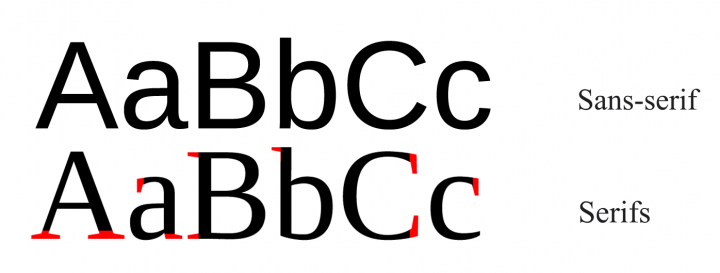
Font serif mirip dengan font sans serif dalam hal memiliki struktur yang stabil dan dapat diprediksi, hanya saja mereka datang dengan tanda di akhir huruf ( serif ).
Serif memiliki sejarah panjang dalam tipografi, itulah sebabnya gaya font ini sering terasa lebih tradisional dan canggih daripada yang lain. Dalam hal di mana Anda dapat menggunakannya, serif dapat digunakan baik di badan atau teks header halaman web.
Alasan lain Anda mungkin memilih serif daripada font lain adalah aksesibilitas. Karena serif dilengkapi dengan tanda di bagian atas dan bawah karakternya, huruf yang terkadang mirip satu sama lain (seperti huruf kapital “I”, huruf kecil “l”, dan angka “1”) mudah dibedakan.
10. Times New Roman
Ketika surat kabar Times of London membutuhkan jenis huruf baru di awal abad kedua puluh, ia bekerja dengan desainer Monotype untuk membuat Times New Roman secara khusus.
Sampai hari ini, TNR digital adalah salah satu font yang paling dikenal, populer dan terbaca di web. Situs web seperti Daily Mail, Huffington Post, dan Wayfair semuanya menggunakannya. Sebagai bonus, ini juga aman untuk web (yang diinstal secara universal di semua perangkat).